Как различить «б» и «в» в рукописном шрифте
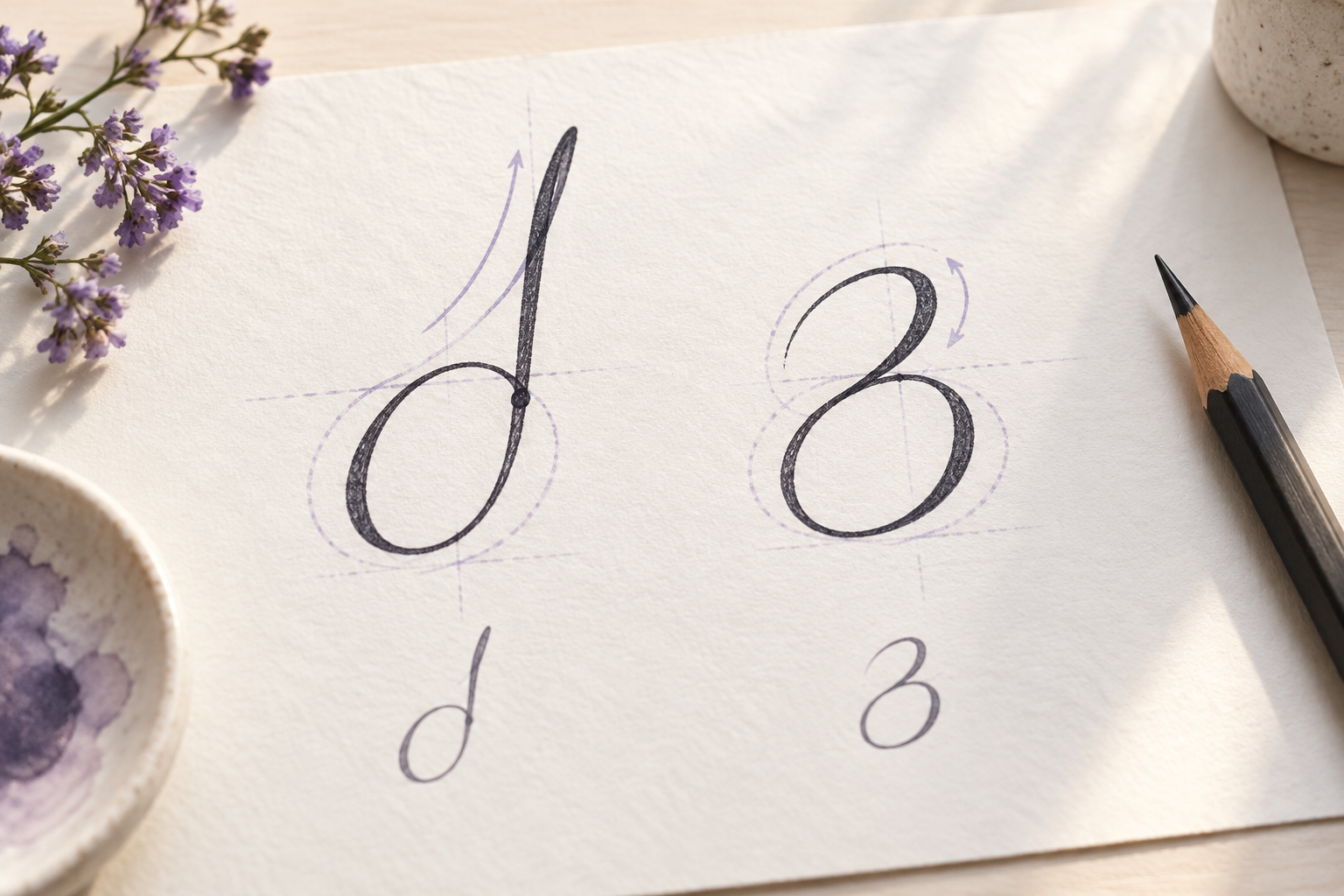
Строчные «б» и «в» в рукописном шрифте могут казаться родственными: обе формы округлые, обе часто имеют петлю, а наклон и соединения дополнительно сближают их. Чтобы читатель не путал «борт» и «ворт» или «был» и «выл», недостаточно слегка изменить ширину одной буквы. Нужно закрепить за каждой устойчивые признаки силуэта, входа, выхода и внутреннего просвета. Ниже — способ спроектировать пару, проверить её в словах и исправить без разрушения общего почерка.
Почему «б» и «в» начинают сливаться
Путаница обычно возникает не из-за одной неудачной детали, а из-за совпадения нескольких решений. Если обе буквы построены вокруг одинаковой овальной петли, имеют одинаковую ширину и одинаково соединяются с соседями, читателю приходится разглядывать мелкие отличия. На крупном кегле такое сходство может быть незаметным; в плотной строке или на экране телефона признаки исчезают быстрее.
У строчной «б» часто есть заметный восходящий элемент над чашей, а строчная «в» обычно читается через компактную верхнюю часть и нижнюю чашу. Это лишь отправная точка, а не единственно возможный рисунок: рукописный стиль может быть наклонным, связным, угловатым или почти печатным. Важно, чтобы выбранные формы оставались различимыми в рамках конкретного почерка и не опирались на одну тонкую черту.
Сначала зафиксируйте узнаваемые признаки каждой формы
До правки очертаний решите, что читатель должен распознавать первым. Для «б» полезно определить характер её верхнего штриха: насколько он поднимается, где меняет направление и как входит в основную чашу. Для «в» задайте устройство верхней зоны и нижнего объёма: они могут быть разного размера, иметь разную точку соединения и разный наклон. Не требуется делать контуры симметричными; требуется сделать различие устойчивым.
- Силуэт: различаются ли общий контур и соотношение верхней и нижней частей?
- Вход: из какого места начинается видимый штрих и куда движется рука?
- Просвет: сохраняется ли разная форма внутренних пространств?
- Выход: можно ли закончить букву и перейти к следующей, не превращая её в другую?
- Масса: не становятся ли обе формы одинаково тяжёлыми после утолщения?
Выберите для каждой буквы два-три признака, которые будут заметны даже без увеличения. Например, «б» может отличаться выраженным подъёмом и широкой нижней чашей, а «в» — короткой верхней частью и более компактным корпусом. Точные пропорции задаёт ваш стиль; полезнее записать принцип, чем копировать одну схему из чужого алфавита.
Настройте петли и просветы, а не только ширину
Когда обе буквы имеют округлые части, небольшое изменение ширины редко решает проблему. Сравните, где находится максимальная ширина каждой формы, насколько верхняя и нижняя зоны отличаются друг от друга и как контур подходит к оси штриха. У одной буквы петля может быть более открытой, у другой — сильнее замкнутой. Разница должна сохраняться и в чёрном силуэте, и в белом пространстве внутри.»
Проверяйте не только пустую внутреннюю область, но и расстояние между соседними штрихами. Если две линии «в» слишком близки, при уменьшении просвет схлопнется и буква станет пятном. Если петля «б» чрезмерно узкая, её верхний штрих может визуально приклеиться к основному корпусу. Не увеличивайте все просветы одинаково: корректируйте ту зону, которая несёт различительный признак.
Согласуйте буквы с характером почерка
Если алфавит связный, сначала посмотрите, как «б» и «в» входят в слово после предыдущей буквы и выходят к следующей. Одинаковый соединительный штрих может скрыть различие, даже если изолированные глифы хорошо спроектированы. Иногда достаточно изменить высоту или место входа, чтобы силуэт читался яснее. В другом стиле, например с раздельным написанием, полезнее развести верхние акценты и ширины чаш.»
Сохраните общий наклон, толщину и степень округлости там, где они связывают алфавит. Отличие не обязано превращать одну букву в инородный знак. Хорошая пара выглядит частью одной системы, но не требует от читателя угадывать, какое слово перед ним. Если заметное различие получается лишь при нарушении общего ритма, вернитесь к конструкции обеих букв и проверьте точки начала и поворота штриха.
Учитывайте и задачу будущего шрифта. В крупной декоративной надписи формы могут быть выразительнее, а в заметках, учебных материалах или длинной подписи важнее быстрое чтение в непрерывном тексте. Это не повод делать одну букву «правильной», а другую упрощённой. Подготовьте нейтральный тестовый фрагмент, набранный именно вашим шрифтом, и проверьте, остаются ли оба силуэта узнаваемыми без знания замысла автора.
Для ручной проверки удобно записывать конкретные наблюдения, а не оценку «нравится» или «не нравится». Например: «верхняя петля теряется в связке перед мягким знаком» или «просвет нижней части закрывается после уменьшения». Такие заметки позволяют сравнить версии и понять, улучшила ли правка чтение, не подменяя задачу вкусовой оценкой.
Различимость «б» и «в» строится на системе признаков: силуэте, петлях, просветах и способе соединения с соседями. Зафиксируйте, чем именно отличаются формы, проверьте их в словах при реальном размере и меняйте по одному параметру за раз. Если вы создаёте собственный почерк как шрифт, Fontgenerator поможет перейти от заполненного шаблона к набору, который можно проверять в настоящих текстах.